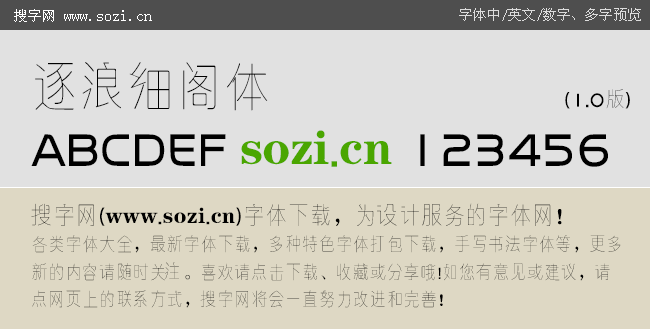
逐浪細(xì)閣體
搜字網(wǎng)提供一款逐浪細(xì)閣體中文藝術(shù)字體下載,逐浪細(xì)閣體是一款用于細(xì)線設(shè)計(jì)方面的字體,結(jié)體寬綽秀美外似柔潤而內(nèi)實(shí)堅(jiān)強(qiáng),形體端秀而骨架勁挺,整體字形筆畫均衡。整體效果十分出色,適合應(yīng)用于廣告設(shè)計(jì)、名片設(shè)計(jì)、包裝印刷、產(chǎn)品設(shè)計(jì)等應(yīng)用。